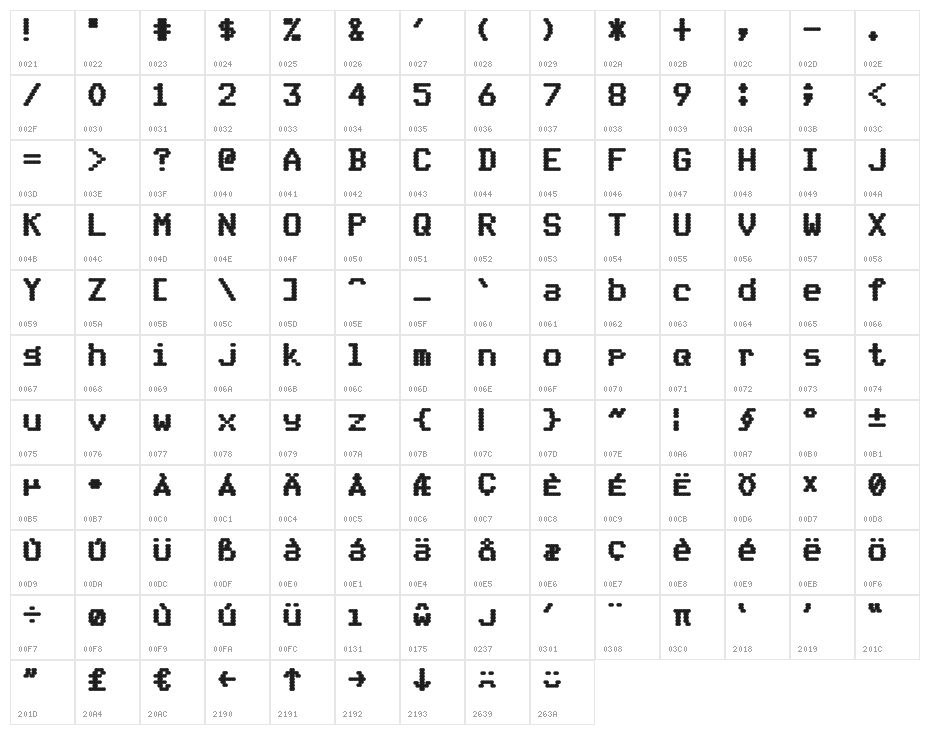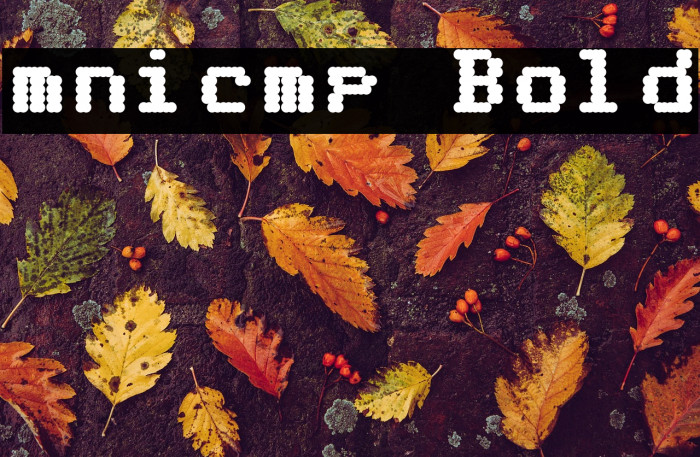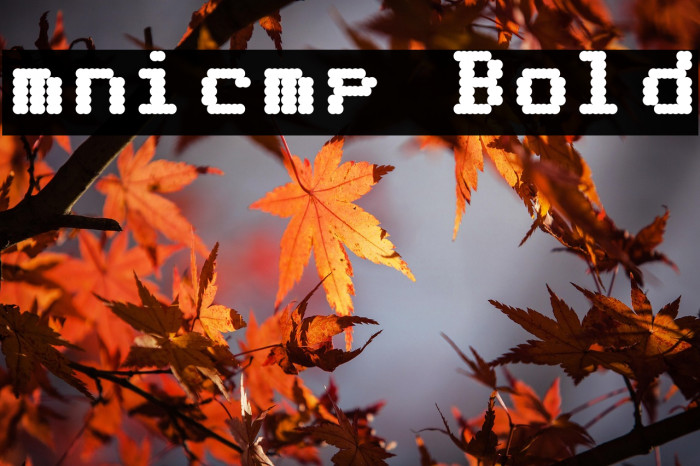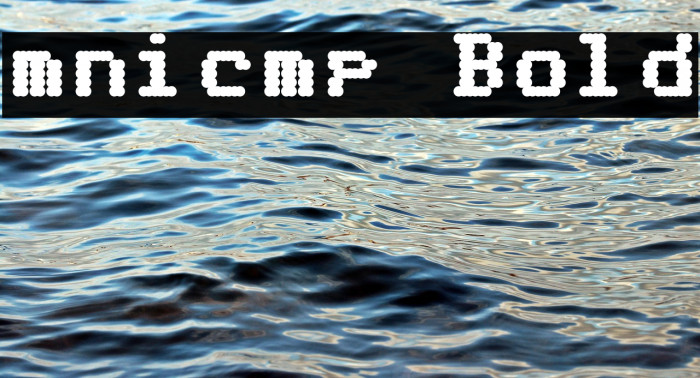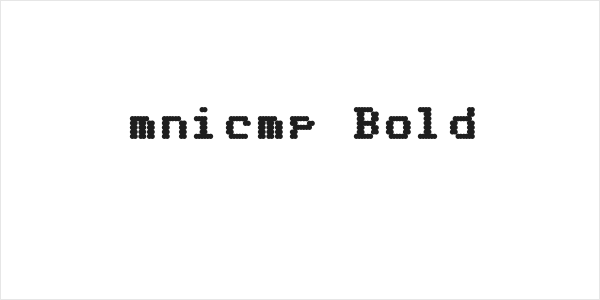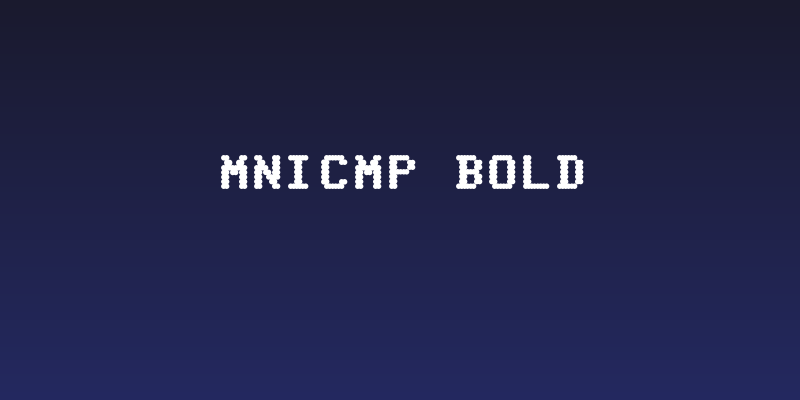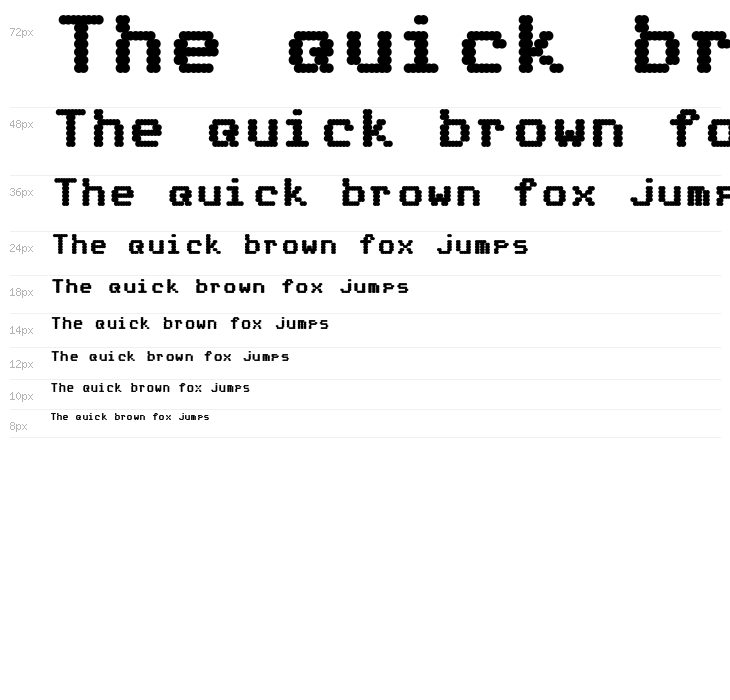
mnicmp Bold Font
| Gesamtstil | Modern, Decorative |
| Anwendungsfall | Logos, Headlines, Posters |
| Vorgeschlagene Projekte | Ideal for digital art projects, children's books, playful branding, and creative posters. |
mnicmp Bold